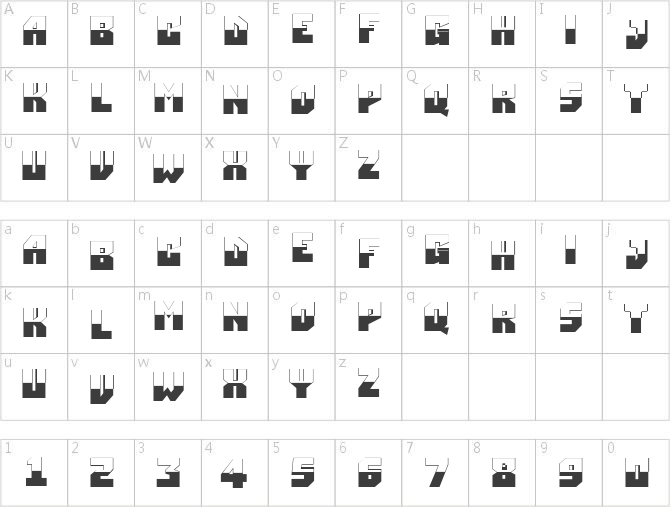
a_simplerbubw bold 詳情頁(yè)
a_simplerbubw bold字體字庫(kù)是一款讓人賞心悅目、百看不厭的英文字體,適合各類(lèi)廣告和產(chǎn)品包裝設(shè)計(jì)應(yīng)用,字體大小0.04MB,格式為ttf字體,上傳用戶(hù)是得·岸,作者/版權(quán)方為未知